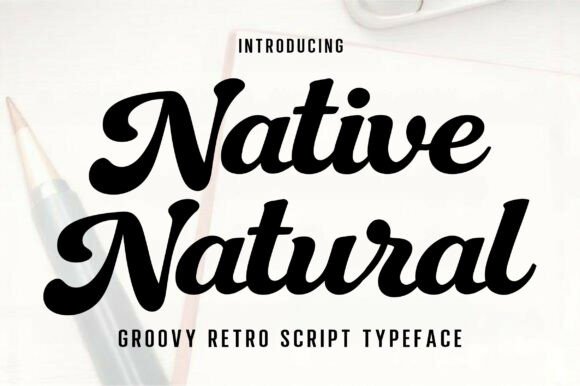
Native Natural
適切なデザイン要素を見つけるのは難しい場合がありますが、Native Naturalは作品を即座に引き立てる優れたコレクションを提供します。
POD(オンデマンド印刷)製品、結婚式の招待状、またはソーシャルメディアのグラフィックを作成している場合でも、Native Naturalは理想的です。